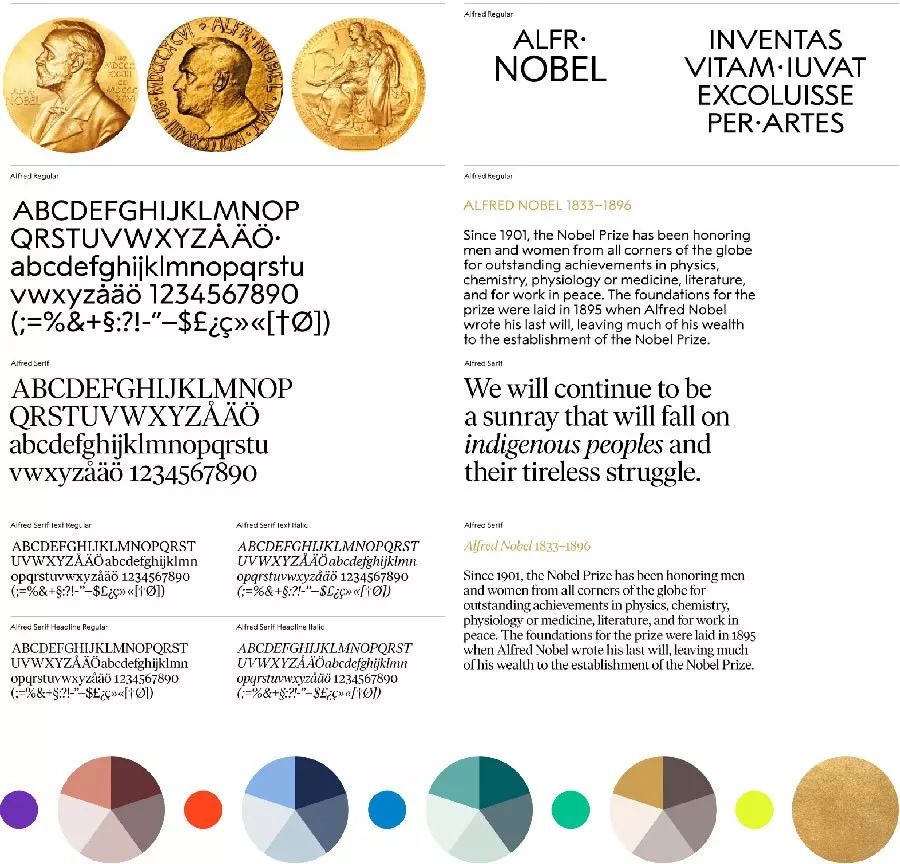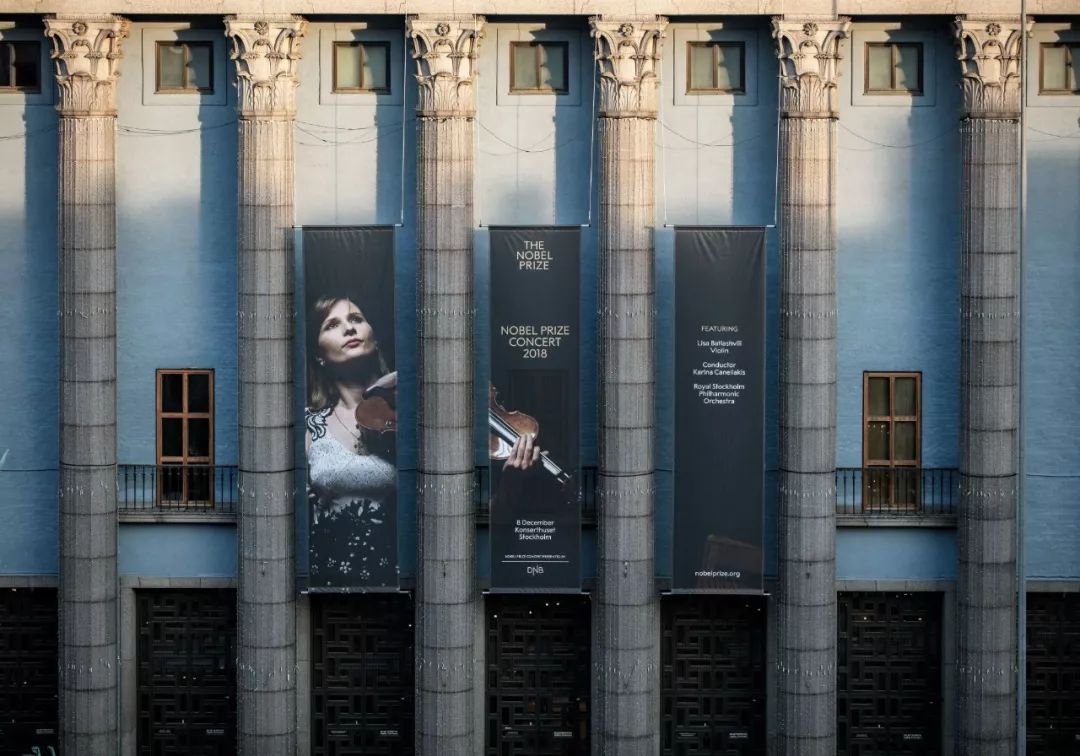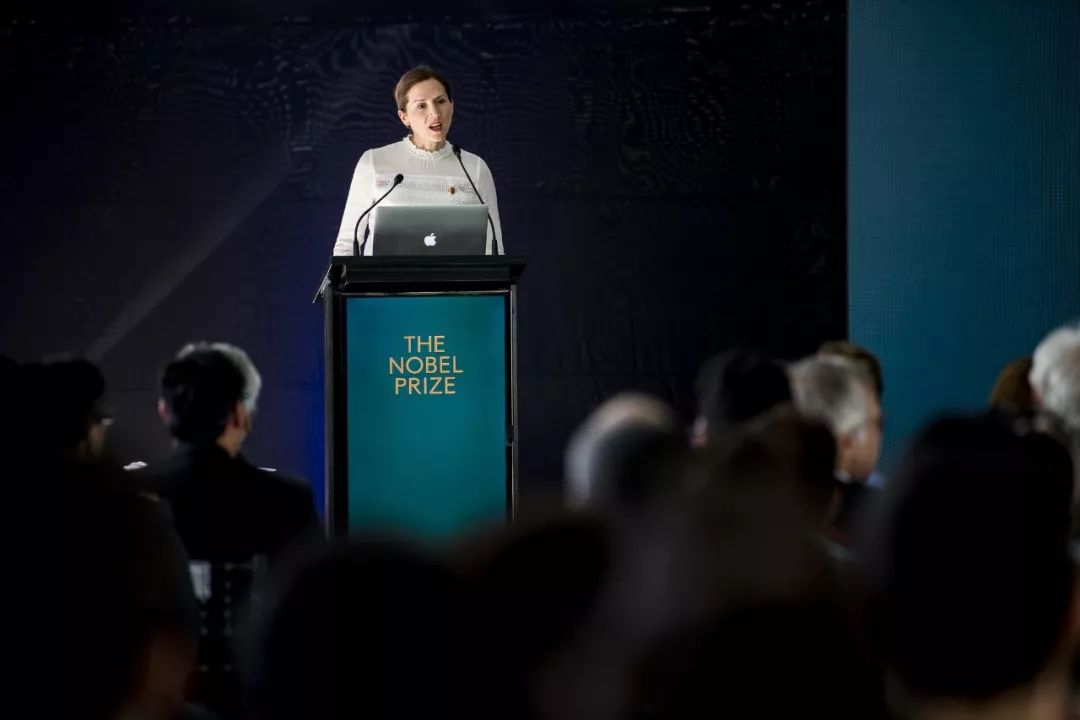
他的设计作品,几乎承包了整个斯德哥尔摩!
来自瑞典的斯德哥尔摩设计工作室Stockholm Design Lab(以下简称为SDL)是一家国际化的北欧风格设计公司。作为北欧最著名的品牌视觉机构之一,毫不夸张地说,SDL的设计几乎承包了整个斯德哥尔摩!
从你搭乘SDL第一个客户SAS的航班,到达由SDL进行视觉设计的机场,随时可能就走进他们的连锁店客户MAX吃汉堡,或者在他们的运动品商店客户Stadium购物,无处可逃。除此,他们的国际客户还包括括IKEA宜 家 、沃尔沃汽车、绝对伏特加、 德国Ustra Stadt- bahn、韩国Hyundai Card、日本Askul、可口可乐等。
创始人Björn Kusosky是AGI(国际平面设计联盟)会员,曾获国际奖项150多个,包括2个戛纳金狮奖、金棕榈奖、亚洲设计大奖金奖、红点奖等,并获得2015年Platinumegg和2014年 Berlingpriset的终生成就奖。SDL为何会被业界奉为 “北欧风格设计教科书般的存在”?瑞典国宝级设计师Björn Kusosky究竟有几把刷子?9件SDL经典作品带你快速了解。
SDL最新力作正是操刀诺贝尔奖的视觉革新,重点在新设计的两套字体与配色的升级。1895年成立以来,诺贝尔光环一直挂在那枚金光熠熠的诺贝尔奖牌。但由于长期缺少统一的视觉标识而导致观感较为零散随意。最近诺奖及其分支机构首次一齐换上了SDL为其设计的整套系统又灵活的视觉形象。其中LOGO的变化最为直观,颇具极简质感的无衬线字体直接替代了原先的诺贝尔头像。主力字体Alfred Sans的灵感来自诺奖奖牌上的经典字体,再参考20世纪早期传统的无衬线字体特点设计而成。配套的衬线字体版本Alfred Serif则与Alfred Sans在功能与美学上进行互补,确保该系统的长期使用。用色上,SDL肯定金色是诺奖的代表色,因此其他配色组的设置则以金色为出发点延伸,延续历史保持优雅的同时更适配数字化的传播需求。
20世纪90年代中期,穿行于瑞典、挪威、丹麦之间已经半个世纪的北欧航空,前景变得不明朗。随着越来越多新的廉价航空公司的崛起,北欧航空的乘客渐渐流失,之前锁定商务游客,为他们提供舒适休息室、并收取企业价格的策略,显得越来越不可行。北欧航空重新寻找定位,并把目标锁定在非商务乘客的市场份额上。要让北欧航空从竞争对手中脱颖而出, SDL的策略是用真正的北欧设计替代之前的美式设计。以往处理LOGO的方式,像往牲口上打烙印一样简单粗暴。SDL摒弃这种做法,将机上各种物品包装、洗手间窗口、制服衣柜等处严肃呆板的名称标识,一律换成美观吸引、丰富通用、内容主导的北欧设计,并印上一句从“北欧航空诗歌库”里选取的简短语句,赋予物件更人性化的设计语言。休息室换成更柔软舒适、居家型沙发;全新的色彩和字体;让人倍感新鲜的图案等,也都给乘客提供全新的更好的体验。从空乘制服到发夹,从机场标识到盐包,SDL和TEA一起,给北欧航空2500个物件进行了全面的重新设计。项目不仅获奖,也持续应用了多年,将整个品牌带到了全新高度。至2005 年时,SDL已经与宜家合作了多年,为宜家研发了一套适用于全部8000个非家具类商品的包装设计系统,并升级了标识,其中包括5种语言的企业字体。
而在这一次的合作中,宜家找到SDL专门针对食品领域设计。品牌希望合并宜家的咖啡馆和食品超市,打造一个瑞典风味的宜家美食品牌,专门售卖各种贴有宜家商标的传统瑞典小食。项目的挑战在于,用视觉设计代替具体的文字说明。尽管销售这些产品的43个国家中,42个是非瑞典语国家,但宜家依然坚持要求每一种产品都只能用瑞典语标注产品名称, 例如Gräddsås(奶油汁),Lingonsylt (越橘果酱),Skarpsilt(鲱鱼)等。SDL设计了三种包装,基本原则是:尽可能地透明化,包装袋设个小窗口或直接用玻璃罐来展示酱料、甜食或水果等商品;在罐头等食物的包装上使用一目了然的插图或轮廓;在需要更多视觉信息时则使用摄影图片。
可口可乐百年庆之际,品牌邀请了来自世界各地的创意人员为其设计庆祝海报,SDL也在受邀之列。
即使碎成碎片,大家也能辨认出可口可乐瓶的形状。在这张海报中,SDL就将整个可乐瓶都模糊化处理以唤起观者的好奇心,同时也证明了具有辨识度的品牌形象的价值。
这件作品在可口可乐公司和美国亚特兰大高级艺术博物馆共同举办的“可口可乐瓶:一个百年美国标志”展览中展出。 同期展出的还有知名设计师兰斯•威曼、Nendo、奈维尔•布罗的作品,除此之外, 还有安迪•沃霍尔的可口可乐经典艺术品回顾展。
2010年,经由Takeshi Akiyama的努力,其祖父50年前被迫关闭的一家小小清酒厂得以起死回生。Takeshi Akiyama听从一位资深清酒大师的指点,重新启用了Ohmine酒厂三百年的配方,用当地的米和清泉,酿制口感清甜、丰富的清酒。配方是老的,但包装可不是。
所有日本超市的清酒货架上,都是清一色传统的棕色、绿色的瓶子,品牌名称大多用黑色书法字写在瓶身标签上 。而Takeshi Akiyama希望自家的清酒在包装上能独树一帜,展现Ohmine独家限量产品,让各国消费者清晰辨认三种不同度数的清酒,最好还能够抵御强光直射,防止变质。
乳白色不透明的瓶子可以确保Ohmine清酒完全不受直射光影响,Ohmine也同意取消标签,用丝网印刷的工艺将产品名称直接印在瓶身上。清酒三种度数的展示形式则是从酿酒发酵的过程得到启发,杂质去得越多,米心就越少,精米度就越高,酿出来的清酒质量就更好,所以瓶身包装以去除杂质后 的精米为形象进行创意:纯米酒的瓶子有三颗米,纯米吟酿有两颗,而纯米大吟酿只有一颗。
白瓶设计引起了轰动,国际媒体争相报道,并获得设计大奖。当然,更实际的是——Ohmine清酒出口至其他国家,广受好评。它不仅入选了米其林三星餐厅的菜单,也成为2013年瑞士达沃斯世界经济论坛的指定用酒之一。
日本人的职场生活中,Askul办公用品随处可见,从纸笔、电池,到包袋、椅子、工具,甚至还有咖啡、面条。Askul成立于1963年,销售超过4万种品类的商品,也通过网站和产品目录提供在线购买和配送服务,24小时内可送达日本各个角落。
2005年,Askul开始寻求新的突破,想为自有品牌商品建立一套清晰、醒目的视觉识别系统。他们希望出来的作品简单、鲜明且实用,这正是瑞典设计和日本设计的共通特质所在,但同时,他们又想要有别于日本设计,给日本人眼前一亮的新鲜感,于是品牌找到 SDL,希望得到一套完整的解决方案。
项目时间非常有限,跨越时区和语言障碍,SDL拿出了一整套包装和产品设计的解决方案,放在Askul网站或产品名录上,简约但有型,每个产品说明都精简到最基本的形式和最基础的信息。Helvetica字体左对齐, 纯色图案,简明标志,字迹清晰的双语标签等,让产品信息在包装上脱颖而出。插图或图案轮廓鲜明,巧妙地告知了消费者产品的类别。
在200多个人们最意想不到的地方,给日常用品做设计,让Askul在全球范围内倍受关注。例如一组电池包装竟然也在社交网络上火爆起来,被网友疯狂转发 。洞察基于人们往往不知道自己所要使用的电池型号,要解决这个问题,就直接把型号放上去就行啦。经过重新设计的电池 ,销量超过了2.3亿,Askul品牌影响力也提升到前所未有的高度。
2010年,瑞典政府对国营药房进行私有化改革。两家私人股本公司联手买下24家医院和医疗机构的门诊药房,再加上手中持有的一 份独特资产小连锁店,凭借产品的信誉保障和连锁店的地段优势,几乎打造了一个 垄断市场。其他新连锁药店在商业街上竞相招揽顾客之时,Vårdapoteket则找来SDL为他们的小型连锁药店创造新意:期待其打造一个让人印象深刻的品牌,一个让人难忘的目的地。
对此,SDL的策略是:从Vårdapoteket消费者的角度出发,在难以找到医疗机构的偏僻之地,为这些远离家门的人,提供一片热情又安静的绿洲。SDL大面积地使用鲜艳缤纷的色块,引入柔和的灯光照明,配以清晰的信息说明;墙上不挂那种健康之家的全家福图片,取而代之的是漂亮墙纸由色彩动人、图案有趣的人体解剖图以及植物插画构成,以此赞美人类神奇而非恐怖的人体器官。
不出所料,Vårdapoteket受到媒体大幅报道,尤其是用彩色人体器官做墙纸这个大胆的创意。这个品牌形象所带来的市场反响也很惊人:2013年,Vårdapoteket营业额增加了30%,还赢得 了县议会住院药房服务的四个投标。
Moderna Museet(以下简称MM),瑞典国立当代美术馆,1958年创立,位于斯德哥尔摩的船岛,因举办过毕加索、杜尚、美国波普艺术等广受好评的展览而名声大噪。
2002年,由于旧址修复和翻新,MM被迫暂时关闭,并趁此空档重新更新自己的视觉识别系统。
新的建筑是一个长型、低矮的盒状结构,由西班牙建筑师拉菲尔•莫内欧设计。
之前平淡无奇又格外复杂的导视系统,已不能满足吸引船岛访客的需求,因此,新的视觉识别不仅要彰显MM的声誉, 还要赋予它亲和力。在50多个北欧设计工作室中,SDL与Greger Ulf Nilsson、Henrik Nygren脱颖而出,被选为美术馆新视觉设计合作伙伴,共同为自90年代以来就一直未定型的MM,创造了一个有着持续影响力的成功的品牌形象。
项目前期,SDL考虑的是一个既拟化MM长线型外观,又清晰展现船岛文化特征的 LOGO。后来又尝试了很多创意,甚至想过直接写两个麦当劳的“M”,或者用金色拱门。最终,灵感源于一个“现成品”——MM25周年(1983 年)纪念册的封面,其设计出自于一直与MM 保持往来的知名当代艺术家罗伯特·劳森伯格。
劳森伯格手写的“Moderna Museet”醒目且富有张力,展现出艺术创作过程,以及艺术界关于真实性的观念,它与MM的过去产生共振,也与它所扮演的先锋角色——举办劳森伯格和60年代的波普艺术运动等展览相呼应。十多年来,这个签名式LOGO让MM重新回归现代艺术版图,并且应用在各种周边产品的设计上。
SDL所设计的导视系统,则采用了荷兰设计师Wim Crouwel 的Gridnik字体特别版,打造了与机场标识类似、可发光的导视牌,在建筑的各个角落为游客提供清晰的指引。
零售连锁集团Venue Retail Group在北欧地区拥有超过150家分店(旗下品牌包括Accent, Morris, Rizzo等),主营鞋包配饰,既售卖各种名牌鞋包,也售卖自有品牌商品,拥有不错人气。
2014年初,Venue Retail Group找到SDL,想要打造一款全新的箱包产品线。经过一番调研,SDL了解到,“旅行必备品”在当时整个市场上都是空白的。SDL决定从这个角度切入,研发可以满足出行者一切需求的产品。从概念到名称,从策略到品牌,从视觉识别到店面设计,一切都是新的。
一个名为A-TO-B的空间,将汇聚并提供人在旅途时最便携、最实用、最棒的单品。有了清晰的定位之后,A-TO-B很快就设计出来了,所有内涵就在LOGO之中,这个现代、有移动指向性、可以灵活变化的LOGO,目的简单明了:从A到B,随身携带。第一家A-TO-B店铺于2015年8月正式营业,多家分店也紧接着陆续开业。